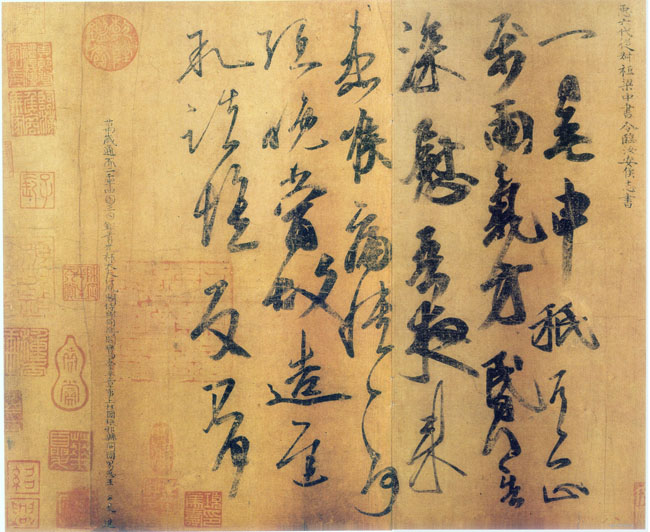
王志
王志简介
字次道,琅琊临沂人。王僧虔子。《梁书》卷二十一《王志传》:“志善草隶,当时以为楷法。”
《一日无申帖》,见于辽宁省博物院藏的《唐摹万岁通天帖》
《一日无申帖》(又称《喉痛帖》)释文:
臣六代从叔祖梁中书令临汝安侯志书
一日,无申只□正
属雨气方昏,得告
深慰。吾夜来
患喉痛,愦愦,何
□晚当故造迟
叙。诸惟□不□。